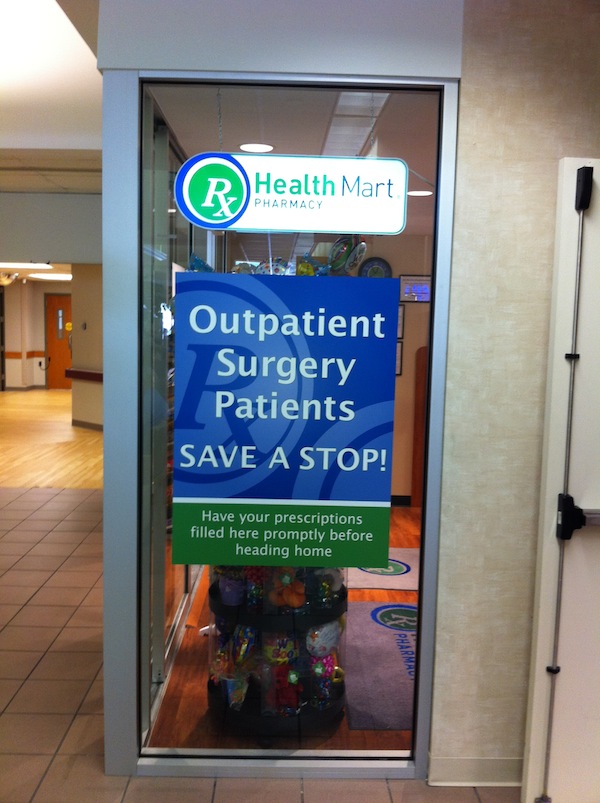
Lira Larum Löffelstiel … die türkische Lira hat ein Symbol.
… aus dem Euro-Zeichen-Desaster.
Wie ich andernorts schon gesagt habe: diese ganze Aktion ist reines Imponiergehabe und komplett überflüssig. Das Ergebnis ist dilettantisch bis zum Koma.
Es gibt seit langem unter 20A4 ein seriöses Zeichen für LIRA, das müßten die Türken nur benützen.
Ich halte das sogar für eine Provokation gegen die EU und ein klares Statement gegen den Euro. Aber da wird es politisch, drum halt ich schnell wieder den Mund. :-|
Bruharhar! Das gibt’s doch nicht! Die […]* sind zu bescheuert, ihr eigenes Währungszeichen zu benutzen!!! Ich lach’ mich tot! :hammer:
Wieso? Wenn ich das richtig verstanden habe, ist das Unicode Zeichen U+20A4 ein generisches Zeichen für Lira, also nicht nur für die türkische Lira. Außerdem sieht des dem Pfund-Symbol sehr ähnlich. Diese beiden Dinge dürften der Grund sein, warum die Türkei ihr eigenes Währungsymbol haben wollte.
Nun rollt wohl auch der Rubel in diese Richtung ...
Meine online leider nicht verlinkbare Tageszeitung Badische Neueste Nachrichten überraschte mich gerade mit der Nachricht, die Russen könnten gerade online über ein Rubelsymbol abstimmen.
Google machte mich da leider nicht schlauer und auch die deutsche Wikipedia schrub dazu nix.
In der englischen Wikipedia ist der Zeichenfindungsprozess immerhin erwähnt, aber wohl nicht aktuell, und in der russischen Wikipedia kann ich leider nur Bilder gucken, weil dieser Sprache nicht mächtig ... Aber den Bildern nach dürfte dort etliches mehr stehen ...
na, einige der vorschläge für das Rubel-Zeichen sehen ja aus, alsob es den Rubel dann auf Rezept gibt, siehe Prescription symbol U+211E ℞
Für mich ist das eine RU-Ligatur und hat keine große Ähnlichkeit mit dem Prescription Symbol (dessen Existenz mir gänzlich unbekannt war und dessen Gebrauch für mich keinen Anwendungsfall hat -- abgesehen vom ärztlichen Geschmiere in Patientenakten).
Für mich ist das eine RU-Ligatur
... wobei neckischerweise das "PY" für uns "Lateiner" den Eindruck macht, als stecke "unser" "R" drin, bei Variant 5 zudem ein "u" ... Ein multialphabetales Design sozusagen ...
Aber wären Variant 4 und 5 nicht glyphengestalterisch zulässige Variationen "desselben" Zeichens, das mal so, mal, so je nach Duktus des restlichen Fonts (insbesondere des "y"), gestaltet würde?
Wenn ich da so an das €-Symbol denke, das ja eigentlich auch strenge Vorgaben hat (bspw. rechte Kanten der beiden Striche und des oberen Bogens auf einer (Schnitt-)Linie), an die sich sicherlich nicht jeder Font hält ...
Prescription Symbol (dessen Existenz mir gänzlich unbekannt war ...
Dieses Prescription Symbol ist eine reine US-Angelegenheit. Dort findet man es als "Apotheken-Logo" u.a. an jedem Drugstore.
Klar sind die Rubel-Logo-Entwürfe PY - Ligaturenm (kyrillisch RU) Aber mir fiel eben die Ähnlichkeit auf.
Dieses Prescription Symbol ist eine reine US-Angelegenheit. Dort findet man es als "Apotheken-Logo" u.a. an jedem Drugstore.
Na ja, nicht wirklich. Vielleicht weil sich das generische ℞-Symbol kaum für die Etablierung einer Marke eignet, haben es gerade die großen Apothekenketten meist nicht im Logo, siehe z.B.
Ansonsten: drugstore ≠ pharmacy :tuschel:
Ich hab das in Fl gerade an einer Walgreens - Filiale gesehen - nicht im Markenlogo, sondern in etwa so wie unser Apptheken A zusätzlich.
An jeder Pharmacy hängt es sicher nicht, aber als »typisch« hab ich es zumindest auch in Erinnerung – auch bei den großen Ketten.
℞ is a symbol meaning "prescription". It is sometimes transliterated as "Rx" or just "Rx". This symbol originated in medieval manuscripts as an abbreviation of the Late Latin verb recipe, the imperative form of recipere, "to take" or "take thus".Literally, the Latin word recipe means simply "Take...." and medieval prescriptions invariably began with the command to "take" certain materials and compound them in specified ways.[4] Today, when a medical practitioner writes a prescription beginning with "℞", he or she is completing the command.
(Wikipedia)
Ich hab das in Fl gerade an einer Walgreens - Filiale gesehen - nicht im Markenlogo, sondern in etwa so wie unser Apptheken A zusätzlich.
Dann war das eine lokale Bemühung. Im landesweiten Gebäude-CD taucht das ℞ nicht auf, siehe z.B. diverse Ladenfassaden.
Hier das Ergbnis:
Meine Unicode-Wette: U+20BB ?
Aber diese Buisinessinsider haben offensichtlich das kyrillische U nicht
gesehen, und daher die RU-Ligatur der unterlegenen Entwürfe zum lateinischen R gemacht.